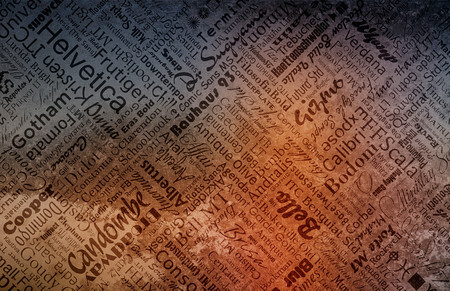
El primero en realizar un proceso de impresión por tipos móviles de metal en Occidente fue el Alemán Johannes Gutenberg que produjo sus primeros impresos entre el año 1448
El siglo XVI es conocido como "la época de oro de la tipografía francesa". Desarrollada entre
1530 y 1585 las novedades tipográficas tienen su origen en Francia en lo que se denomina Edad de Oro de la
tipografía francesa y aparte de ediciones a mano, muestra una creación de tipos verdaderamente interesante. -
Tal fue la importancia de la tipografía, que en 1692 el rey Luis XIV ordenó la creación de un
comité de eruditos para la creación de un nuevo tipo que fuera diseñado bajo principios científicos. El
resultado fue el tipo Jaugeon, de concepto racional, con letras de perfecto eje vertical. -
La innovación tecnológica importante fue el tipo sans serif, que si bien había aparecido en
un catálogo publicado por William Caslon IV en 1816, no causó impacto hasta tiempo después. Criticadas al
comienzo por su simpleza, tuvieron diferentes nombres (góticas americanas, sansurryphs, grotescas,
dóricas), pero terminaron imponiéndose gracias a su alta legibilidad. -
La aparición de las computadoras y sistemas informáticos los que cambiaron todo para
siempre. La litografía offset hizo que los tipos de metal fundido comenzaran a desaparecer de circulación y la
venta del Apple Macintosh en 1982 fue el primer sistema operativo que mostraba diferentes tipos de letra para
elegir y aplicar en las hojas de texto, lo cual fue una revolución.